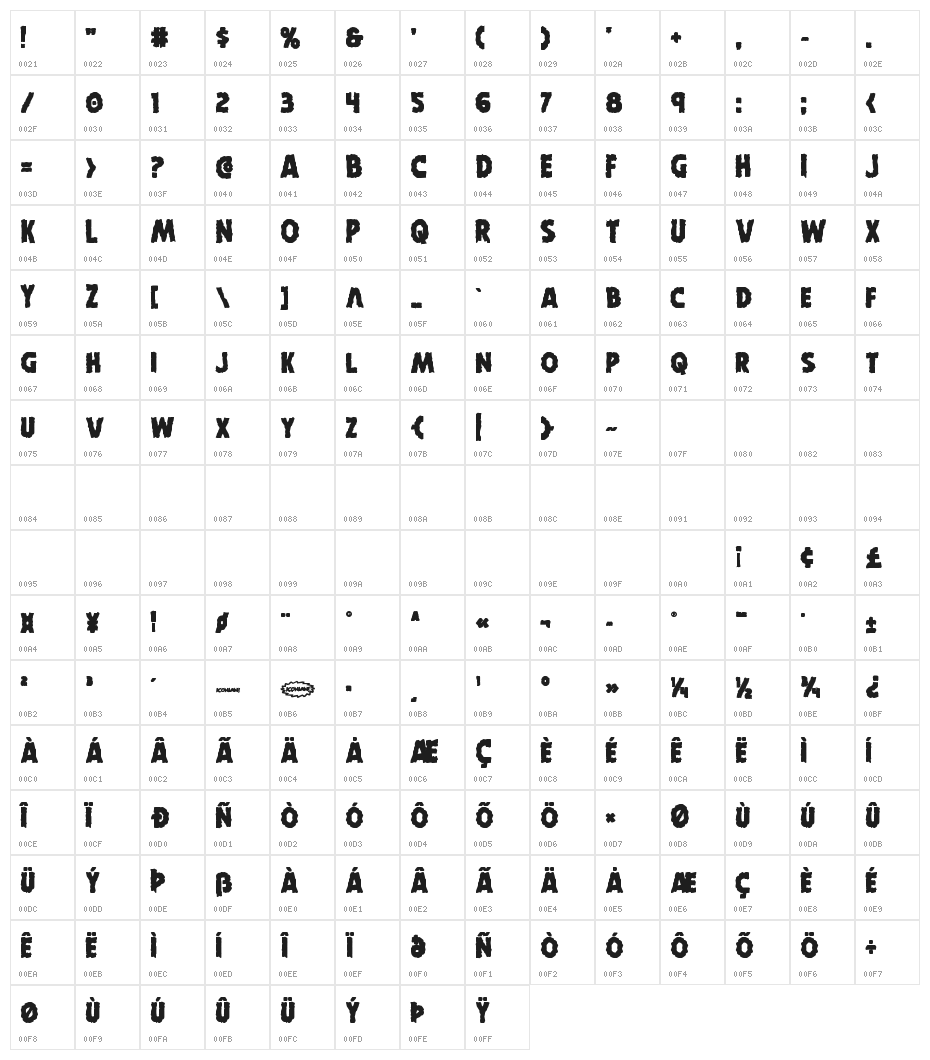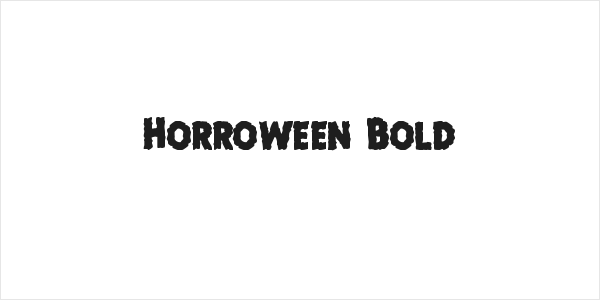
Horroween Bold Font
| 推荐项目 | Perfect for Halloween-themed posters, party invitations, horror movie titles, haunted house signage, and spooky event branding. |